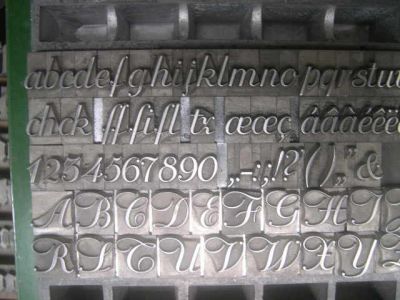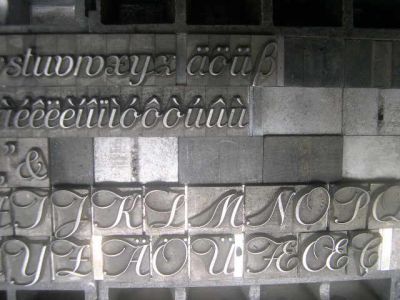
Ich finde sie nicht...
Mike Yanega vermutet eine Friedrich Poppl-Schrift, erwähnt die (aber nur ähnliche) Poppl Exquisit.
Weiß jemand von Euch Rat?
Ohne eindeutige Klassifizierung hat diese Schrift für mich kaum Wert.
Gedreht und gespiegelt:
Ich würde mal sagen, dass ist die „Phyllis“.
Vielleicht in einer kleinen Abwandlung.
Du meinst die Bleisatz-Version, die Wieynck Kursiv von der Bauerschen Gießerei, 1911. Ich glaube nicht, daß es die ist. Die Gemeinen sind ganz anders. Im Seemann ist das Wort "Hamburg" abgebildet. Weder das Gemeine a, noch das Gemeine g kommt auch nur annähernd an die Bleisatz-Schrift heran.
Gleich der Eingangstext vom Klingspor-Museum zu Heinrich Wieync ist in der Phyllis gesetzt. Man sieht es auch z.B. am Versal-M:
Bei dieser Schrift müsste es sich um die mir als "Comtess Lola" bekannte
Schrift der Norddeutschen Gießerei, Berlin O 34, damalige Tilsiter Straße,
handeln. Ich erinnere mich daran, weil ich 1972 meine Hochzeitsanzeige
daraus gesetzt habe. Die Schrift muß in den 30er Jahren entstanden sein.
Sollte ich irgendwann bei mir noch ein Schriftmuster davon finden, würde ich mich melden.
Bei dieser Schrift müsste es sich um die mir als "Comtess Lola" bekannte
Schrift der Norddeutschen Gießerei, Berlin O 34, damalige Tilsiter Straße,
handeln. Ich erinnere mich daran, weil ich 1972 meine Hochzeitsanzeige
daraus gesetzt habe. Die Schrift muß in den 30er Jahren entstanden sein.
Sollte ich irgendwann bei mir noch ein Schriftmuster davon finden, würde ich mich melden.
Aber die "Comteß Lola" ist es nicht.
Dort wird eine "Comteß Lola" gezeigt mit einem vollständigen Versal-Alphabet. Die Schrift ist ähnlich der Bleisatz-Schrifte, aber leider nicht identisch.
Das ist eine harte Nuß. Ich suche bestimmt schon seit drei Monaten.
Am Freitagabend gebe ich sie zurück ins Blei (wird sie eingeschmolzen).
Eine Bleisatz-Schrift, die sich nicht klassifizieren läßt, ist inakzeptabel.
Der Akt des Wiedereinschmelzens symbolisiert den Kreislauf des Seins.
Setzt gleichzeitig ein Fanal des Widerstandes gegen den "Aufstand der (Selbst)gerechten" und ihrer hörigen Totschweiger.
Eine Bleisatz-Schrift, die sich nicht klassifizieren läßt, ist inakzeptabel.
Ich kann Dir leider auch nicht helfen, wollte jedoch nur kurz meine Sympathie mit der Schrift bekunden, die sich nicht klassifizieren lässt! Ich mag Dinge, die in keine Schublade passen.
Versteh nur Bahnhof und Einschmelzen?
Einfach Blei zu Blei, mit dieser unbekannten Schönheit?
PS: Eine Frottage als Andenken wäre tröstlich.
Heute am Spätvormittag bekam ich einen Anruf eines Graphiker-Kollegen aus Düsseldorf, der sich große Sorge wegen meines angekündigten Einschmelzens dieser seltenen und wunderschönen Bleisatz-Schreibschrift machte und wir führten ein für mich sehr interessantes längeres Telefonat. Der Kollege ist Forum-Teilnehmer, aber nach eigener Aussage eher lesend als schreibend.
Fazit:
Der Kollege wird eine Patenschaft für diese Schrift übernehmen, von der ich zwei Schriftschnitte, 24 p und 28 p,besitze. Mittlerweile habe ich einen vollen Zeichensatz in 28 p abgesetzt und werde diesen im nächsten Monat andrucken.
Zur Patenschaft gehört für mich die Verpflichtung, diese beiden Schriftsczhnitte bis zu einer Klassifizierung (Name der Schrift, Schriftgießerei, Erstguß-Jahr, Name des Entwerfers) in meinem Lager archiviere.
Der Pate wird sich von der ordnungsgemäßen Archivierung bei einem persönlichen Besuch des Preußischen Bleisatz-Magazins in der nächsten Woche überzeugen. Hierbei wird - einmalig und ohne dadurch einen allgemeinen Präzedenzfall zu schaffen, auf den sich zukünftige Besucher berufen können - auf den ansonsten obligatorischen Fahnengruß der Preußenflagge am 6,30 m hohen Flaggenmast vor dem Eingang verzichtet.
Sollte die Schrift je eindeutig klassifiziert werden, hat der Pate ein Anrecht auf Überlassung der Satzform mit dem Zeichensatz der Schrift.
wenn sie wirklich niemand kennnt, wäre es potenzial für eine digitale schrift.
Bleisetzer Script :D
"Preussen Script" das wäre was.
Wegen des prophylaktischen Kotaus vor den Anglophilen mit Doppel-s? :D Aber dann steigt mir die ß-Lobby aufs Dach.
Mag sie auch, die happigen Enden. Speziell, wenn sie sogar diplomiert werden, was ich im Kino (oder vor der Glotze) so noch nicht erlebt habe ...
Andererseits frage ich mich aber, wie's wohl Georg dabei wirklich geht? Happy End? Nicht seine Sache! Oder etwa doch? Hartschaliges Weichblei, preußisches?